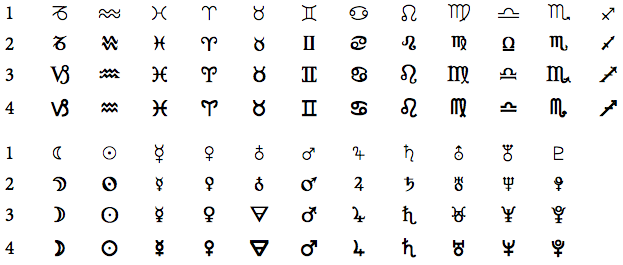
Astronomische/-logische Symbole für die Minion
Ich bin auf der Suche nach Astronomischen Symbolen, die zur Minion passen. In LaTeX habe ich zwar eine Auswahl aber so richtig perfekt passt kein Set:
In meinen Augen passt 3 ganz gut. Aber vielleicht hat ja jemand noch eine andere Schrift, deren Symbole besser passen.
Danke für den Tip, leider haben die dann nur die Tierkreiszeichen und nicht die Planeten. Erstere sind dann häufig auch als „richtige“ Zeichnung und nicht als Symbol vertreten …
Das hat mich aber auf die – eigentlich naheliegende – Idee gebracht, mal meine Schriftsammlung nach diesen Symbolen durchzuschauen und dabei hab ich die Linux Libertine und die Tierra Nueva gefunden. Letztere passt recht gut finde ich, was meint ihr?
Tierra Nueva passt formal (Linienführung, Detailformen) "so ein bisschen" zur Minion ... nicht daneben, aber auch nicht ganz nahe.  Es kommt natürlich darauf an wie die Mischung im Detail aussieht.
(ich glaube für Saturn hatte ich noch eine alternative Version – bin mir nur nicht sicher ob sie am Ende drin geblieben ist oder nicht, sitze grade nicht am Rechner an dem ich das nachsehen könnte)
Hallo Sebastian, wie schön, dass man manchmal direkt mit dem Gestalter einer Schrift sprechen kann :-) bisher haben wir uns, d. h. mein Freund, dessen Arbeit es ist, die ich setzte, und ich uns für die Libertins-Symbole entschieden, die passen zwar nicht so schön, wie deine, sagen uns von den Grundformen aber mehr zu: Insbesondere der Mond und der Schütze der Libertines gefallen uns besser, auch der „Kopf“ des Löwen könnte etwas kleiner sein und das Symbol für Venus geht bei der Libertins etwas unter die Grundlinie, das ist auch ganz hübsch. Dafür ist die Sonne der Libertine im Vergleich zu den anderen Symbolen viel zu klein, weshalb ich im Moment eine bunte Zwiebelfischsuppe koche …
Vielleicht hast du ja Zeit und Lust für Mond und Schütze noch Alternativzeichen einzubauen?
Ich würde die Tierkreiszeichen und Planeten benutzen,
die Du unter '1 wasysym' verwendet hast.
Sie sind in ihrer Darstellung klarer und drängen sich nicht
in der Vordergrund.
Hm … also ich finde, dass sie sich, wegen des völlig anderen Duktus, schon irgendwie hervortuen. Besonders im Fließtext, zumal sie dort auch Lücken hinterlassen, wegen des geringeren Grauwertes …